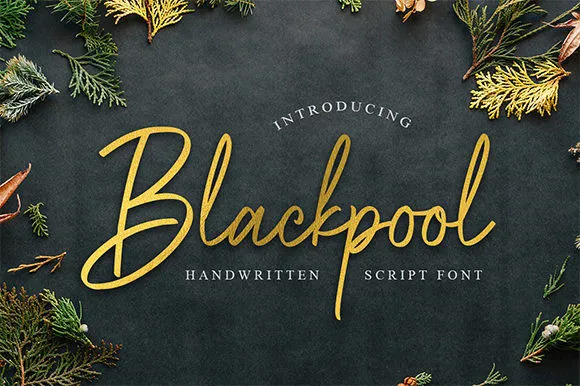
Escreva a descrição do download para a página da fonte Blackpool Handwritten Font neste formato conciso e envolvente: Agradecemos por olhar a nossa nova Blackpool Handwritten Font. Esta é uma linda fonte de escrita casual, perfeita tanto para projetos pessoais quanto corporativos modernistas. Blackpool Handwritten é um belo script elegante que transmite emoção e estilo. Perfeito para logo e identidade visual, cabeçalhos grandes e embalagens de produtos. Seu modo audacioso e divertido vai inspirar e atingir seus leitores. Ideal para quem procura uma fonte casual mas com um toque sofisticado para suas criações gráficas. Neste catálogo de fontes, você encontrará uma escolha perfeita que irá transformar seu projeto em algo único e memorable. Blackpool Handwritten não apenas é versátil, mas também capaz de transmitir a emoção necessária em um design. Sua sofisticação se mistura com uma sensação moderna, tornando-a uma opção excelente para qualquer tipo de projeto visual.